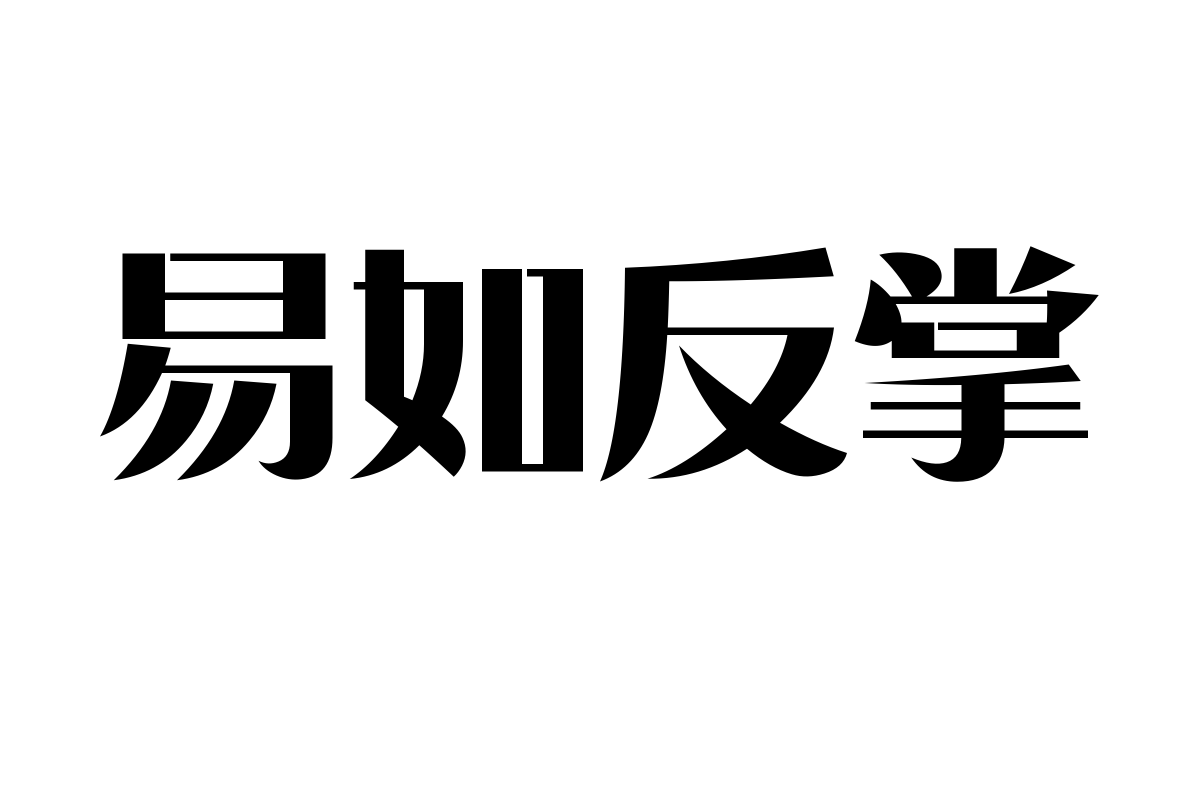
本墨今宋字体是一套由北京华文字库有限公司开发的现代中文字体,它结合了宋体和楷书的特点,形成了一种既具有古典韵味又不失现代感的设计风格。
本墨今宋字体的特点包括:
– 字形规整,笔画清晰,易于阅读。
– 结构紧凑,空间分布合理,适合用于各种印刷品和电子屏幕显示。
– 具有较强的视觉冲击力,能够吸引观众的注意力。
– 适用于商业、教育、出版等领域的字体设计。